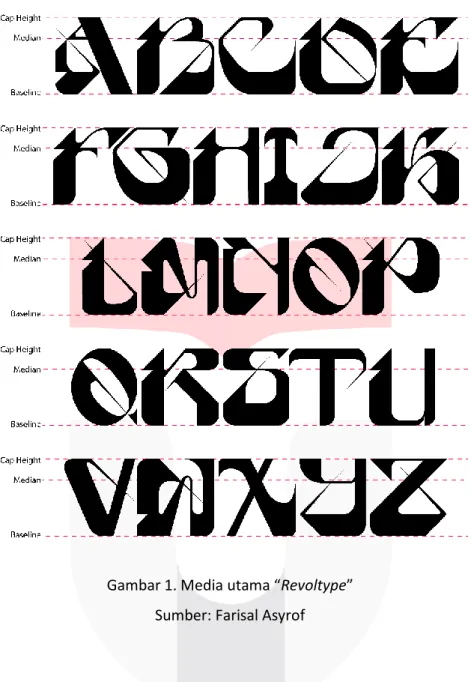
PERANCANGAN TYPEFACE EKSPERIMENTAL BERDASARKAN PERUBAHAN GAYA VISUAL DI KOTA BANDUNG
Abstrak: Kota Bandung mengalami dua babak gaya visual yang berbeda namun sangat berpengaruh hingga saat ini, yaitu era kolonial dan subkultur. Pada era kolonial kota Bandung sangat di dorong kuat oleh penggayaan barat, namun ada pula penggabungan gaya barat dan lokal atau ekletik. Pada tahun 90-an subkultur di kota Bandung sangat masif pergerakannya, hal tersebut ditandai dengan menjamurnya distro pada busana, zine pada media literasi, dan musik bawah tanah. Penggunaan typeface pada kedua babak tersebut pun dapat memberikan nilai peradaban yang pernah ada di kota Bandung hingga saat ini. Sangat disayangkan saat ini kedua babak gaya visual yang berpengaruh besar terhadap kota Bandung tersebut kurang tereksplorasi saat ini.
Dengan adanya typeface eksperimental ini diharapkan dapat mengeksplorasi kedua babak gaya visual tersebut sebagai acuan dalam perancangannya serta dapat meningkatkan eksistensi gaya visual tersebut pada masyarakat kota Bandung.
Abstract: The city of Bandung has experienced two distinct but very influential stages of the visual style to this day, namely the colonial and subcultural era. In the colonial era the city of Bandung was strongly driven by western styles, but there was also a combination of western and local or eclectic styles. In the 90s, the subculture in Bandung had a very massive movement, this was with the proliferation of distriboution outlet in fashion, zines in literacy media, and underground music. The use of fonts in both stages can provide values for the civilization that has existed in the city of Bandung to date. It is very showing that the two stages of visual style that have a big influence on the city of Bandung are currently not being explored. With this experimental face type, it is hoped that the two visual styles can be explored as a reference in the design and can improve the existence of this visual style in the people of Bandung.
PENDAHULUAN
Sejak era kolonial, Kota Bandung dipengaruhi oleh banyaknya perubahan gaya visual. Bandung merupakan titik lebur perilaku, norma, dan praktik sosial-budaya sehingga hal tersebut membawa banyak perubahan dalam kehidupan masyarakat Kota Bandung. Saat ini, Kota Bandung sangat cocok dikatakan kota Kosmpolitan karena banyaknya pengaruh budaya barat yang dijadikan penduduknya sebagai budaya dalam berkehidupan dan cara berpikir internasional. Oleh karena itu, saat ini masyarakat Kota Bandung sudah tidak bisa dikatakan relevan dengan kata kolonial. Beriringan dengan perubahan zaman dan kultur-budaya, generasi pada saat ini sangat kental dengan kebudayaan barat yang dianut pada keseharian mereka.
Wajah Kota Bandung saat ini sudah begitu terlihat modern dengan banyaknya pengaruh penggayaan barat. Gedung-gedung tinggi, gaya arsitektur modern, dan
fasilitas umum kota yang mengacu kearah penggayaan barat. Tetapi dibeberapa sudut kota di Bandung, kita tetap dapat merasakan atau bernostalgia bahwa Kota Bandung merupakan kota bekas jajahan kolonial Belanda.
Salah satu cara untuk mengidentifikasi gaya visual di kota Bandung untuk mengingat kembali bahwa wajah asli kota Bandung merupakan kota bekas jajahan kolonial adalah melihat arsitektur bangunan-bangunan heritage yang tersisa saat ini, salah satu gaya tersebut adalah gaya ekletik. Penggayaan ekletik pada pendekatan arsitektur bangunan di kota Bandung umumnya berkiblat ke berbagai langgam yang telah ada pada masa itu, namun yang paling marak di jumpai adalah langgam Art Deco. Di kota Bandung beberapa bangunan dengan gaya konstruksi eropa kerap kali disilangkan dengan model bangunan tropis nusantara. Sebagai contoh adalah aula barat-timur ITB dan gedung sate, kedua bangunan tersebut merupakan bukti jelas kesuksesan perkawinan arsitektur barat dan timur. Hal tersebut dapat dijadikan langgam baru yang mampu memberi makna terhadap estetika visual pada bidang arsitektur. Banyak pula bangunan-bangunan berlanggam Art Deco pada saat itu yang digabungkan dengan gaya tropis lokal, hal tersebut paling mudah dilihat jika kita melihat bentuk bangunan ekletik ini yang sangat kental dengan Art Deco yang seharusnya memiliki atap datar namun bangunan ini atapnya berbentuk segitiga atau trapesium sama kaki dengan wajah gaya barat tersebut.
Seiring berjalannya waktu sebagai kota titik lebur budaya, Bandung mengalami perubahan gaya visual pada tahun 1990. Hal tersebut begitu terasa kuat ditandai oleh munculnya anak-anak muda yang memiliki gaya yang unik dan berbeda pada praktik budaya utama. Perubahan gaya tersebut dipengaruhi kuat oleh masuknya subkultur ke kota Bandung. Brent Luvaas (2012) mengatakan bahwa anak muda Indonesia saat itu mengadopsi kultur-budaya barat dan menerapkannya menjadi praktik produksi budaya.
Menurut Idhar Resmadi selaku pengamat musik dan subkultur di kota Bandung, pada era 1990-an pengaruh budaya subkultur di Kota Bandung sudah sangat terasa dan beragam. Mulai dari fashion, media literasi, dan musik. Subkultur dapat di identifikasi melalui gaya visualnya, mulai dari cara berpakaian ataupun atribut yang digunakan.
Contoh mudah mengidentifikasi pelaku subkultur adalah melihat tampilan anak punk yang identik dengan potongan rambut mowhak (rambut yang mendongkak ke arah atas), jaket denim dengan berbagai bordir grup musik idola, sepatu boots, dan piercing.
Menurut mereka identitas yang kuat tersebut merupakan identitas atau semangat punk yang melambangkan perlawanan, anarkisme, dan anti kemapanan.
Subkultur di kota Bandung memiliki masa kejayaan sendiri pada tahun 1990-an. Hal tersebut ditandai dengan munculnya distro di bidang fashion, zine sebagai media literasi, dan acara musik Hullaballo, Gorong-Gorong, Punk Rock Party, dan Bandung Minoritas yang seluruhnya dilaksanakan di GOR Saparua merupakan acara terpopuler pada masa itu. Gaya visual subkultur sangat terasa dikarenakan meningkatnya atensi pada masyarakat terhadap subkultur tersebut. Dikarenakan membengkaknya antensi tersebut, terciptalah gaya visual pada kota Bandung dengan sendirinya melalui para pelaku ataupun kelompok subkultur yang ada pada masa itu.
Pada kedua babak gaya visual tersebut, sangat erat kaitannya dengan penggunaan typeface. Pada era kolonial di kota Bandung, hampir seluruh gedung-gedung penting saat itu seperti pusat pemerintahan atau tempat hiburan memiliki nama gedung pada bangunannya, umumnya gedung-gedung tersebut menggunakan huruf sans-serif sebagai tanda atau nama gedung. Pada era subkultur pun penggunaan typeface dapat sekaligus merepresentasikan berbagai macam subkultur yang ada. Hal tersebut membuktikan bahwa typeface mampu memberikan informasi tentang adanya peradaban dari masa ke masa pada suatu kota.